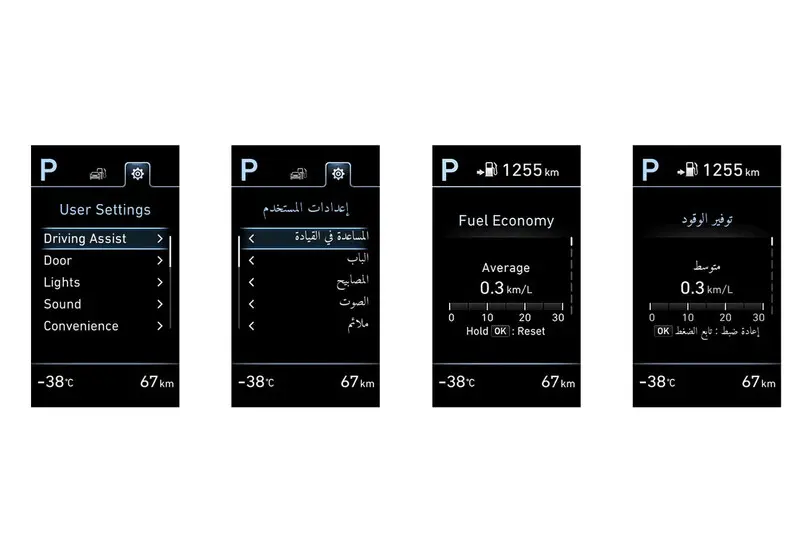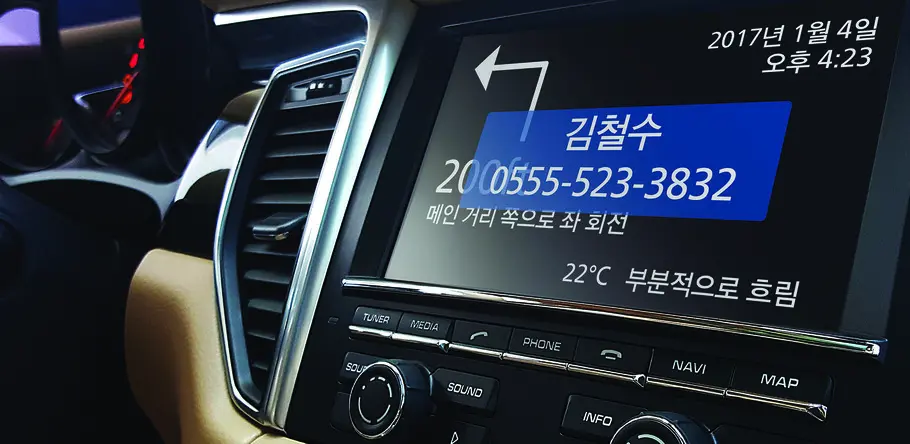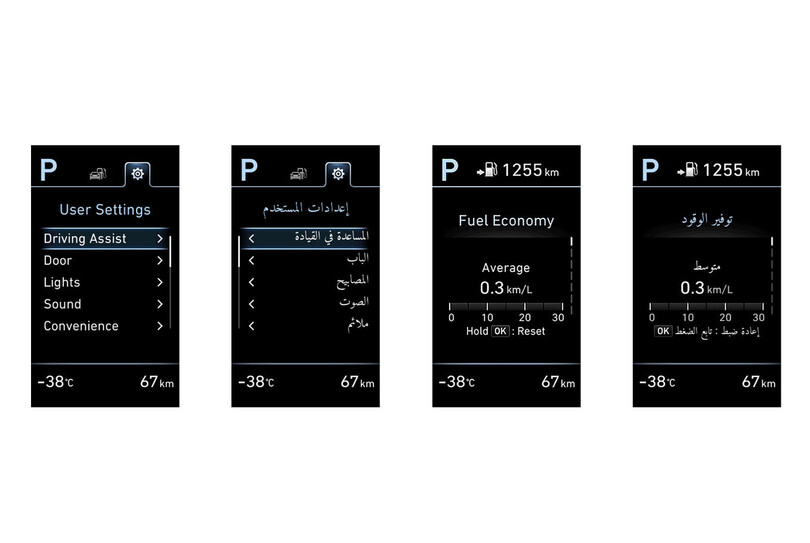
進化する自動車インターフェース:株式会社デンソー
株式会社デンソーは、韓国や米国の主要自動車メーカーに部品を供給する世界屈指の自動車部品メーカーです。Monotypeは組込み技術とディスプレイ表示用書体のノウハウをデンソーに提供、シャープで視認性の高い車載用ディスプレイの開発をサポートしています。
課題:現代のニーズに合った車載用ディスプレイの開発
スマートフォン主流の今の時代、ユーザーがディスプレイに求めるものは、最新のタブレットでも車のダッシュボードでも同じく、シームレスであること、そして鮮明さです。車載用ディスプレイは単に情報を表示するだけの機能から、エンターテインメントを提供し、コミュニケーションのハブとして機能するものへと進化してきています。こうした背景の中で、ディスプレイに表示される文字の瞬読性はますます重要となっています。メモリ容量が限られる車載用ディスプレイにとって、見た目にも美しい高品質のインターフェースの開発はこれまでになく大きな挑戦です。自動車メーカー各社にはすでにリソースの厳しい制約がある上に、世界市場向けに車1台につき20以上の言語対応を求められることも少なくありません。
解決策:複合的なアプローチ
これからのディスプレイに求められるのは一層の個別化・ハイテク化であると考えたデンソーはMonotypeに協力を依頼、この流れに機敏に対応しました。Monotypeは車載専用書体と組込み技術を提供し、デンソーのブランドイメージに合った、新しいドライビング・エクスペリエンスを実現する製品の開発をサポートしました。
スケーラブル技術
デンソーが採用したのは、Monotypeが開発したレンダリングエンジン、Sparkです。低容量フォント専用のSparkは、ビットマップフォントではなく、スケーラブルフォントでの表示を可能にし、メモリの節約に貢献します。デンソーの韓国におけるグループ会社、デンソーコリアでもデジタル計器クラスタにMonotypeの高性能フォントエンジンiType を導入、美しいインターフェースを実現しています。
多言語への対応
デンソーでは20以上の言語に対応するため、MonotypeのWorldType Layout Engine(WTLE)も導入しています。デンソーは、多言語の中でも複雑なつくりのアラビア文字を正確に表示できるフォントエンジンを求めていました。アラビア語では文章は右から左に、数字は左から右に書き、文字は文脈に応じてさまざまに変化します。結果、フォントファイルは大きくなり、デバイスの動作も重くなってしまいます。WTLE ではこうしたアラビア語などの非ラテン系文字のシェイピングが可能です。さらに、Monotypeのフォントリンク技術によって複数言語の文字を1つのフォントファイルに格納できるため、実行時の性能と順応性が向上し、デバイスの小型化とコストの削減が実現します。
車載専用書体の開発
Monotypeは、車載機器にプレミアム車にふさわしい個性とアイデンティティを与えるというデンソーの方針を受け、デンソーの主要取引先自動車メーカーの一部高級車向けに、DIN Nextをベースにした車載専用書体、New HD2.0を開発しました。
視認性研究でリード